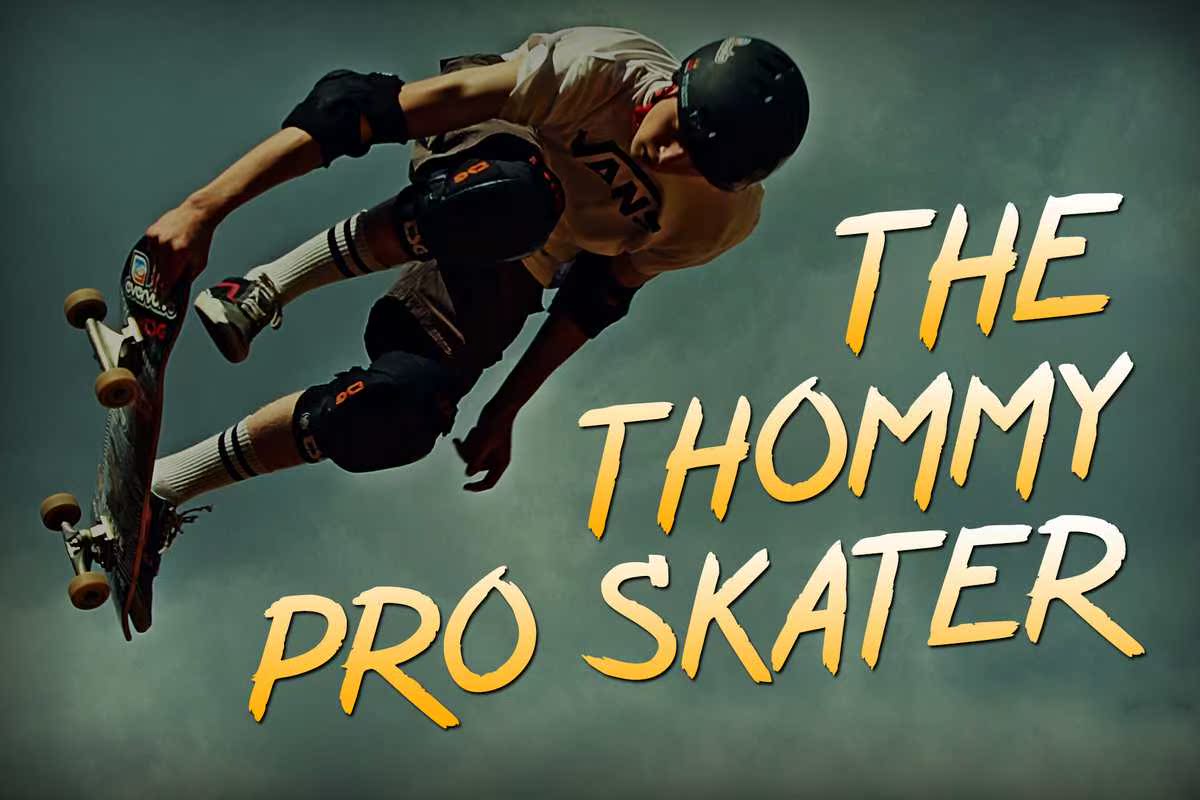
Kurazan是一款全新的手写字体笔刷,优雅且具有年份特征。字体包括完整的大写字母和小写字母,以及多语言支持、通用数字、数字和标点符号。完全适用于签名、文具、徽标、排版、杂志封面、网站标题、传单、服装、品牌、,包装设计和更多。Kurazan是一个全新的手写字体画笔、优雅和年份符号字符集。字体包括完整的大写字母和小写字母,以及多语言支持、通用数字、数字和标点符号。完美地匹配了字体、文具、徽标、排字引号、杂志封面、网站标题、传单、服装、品牌、,包装设计和更多。